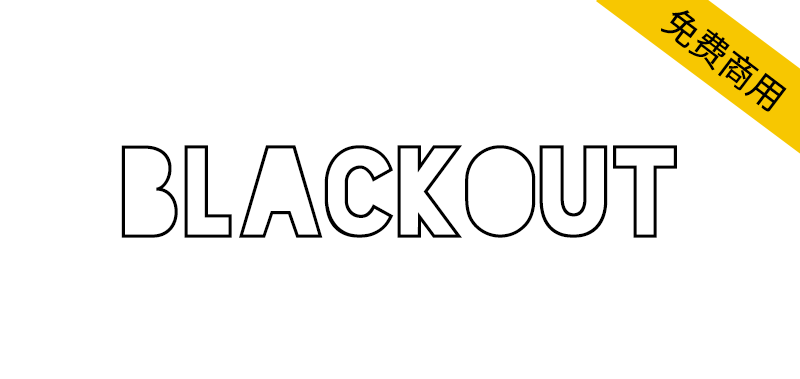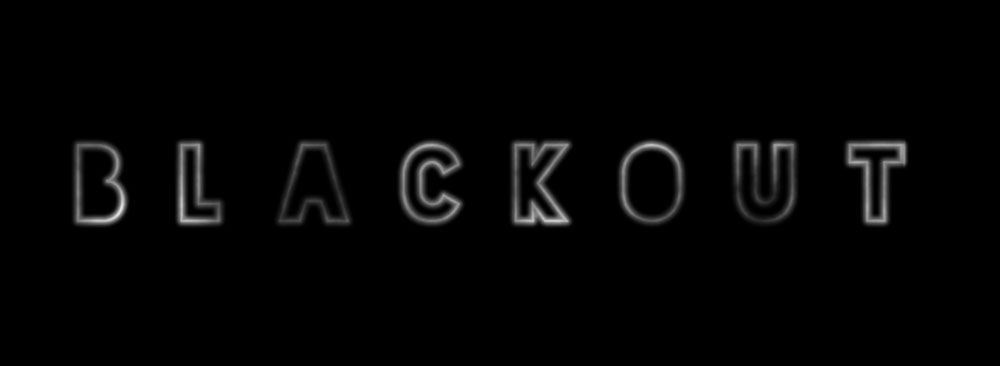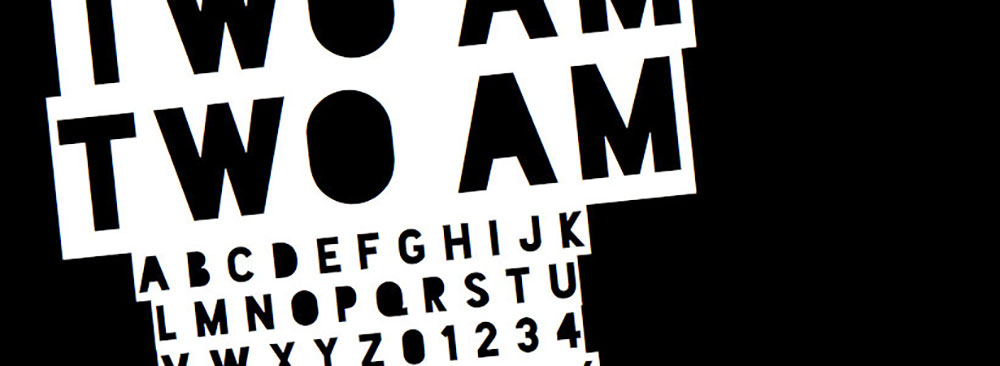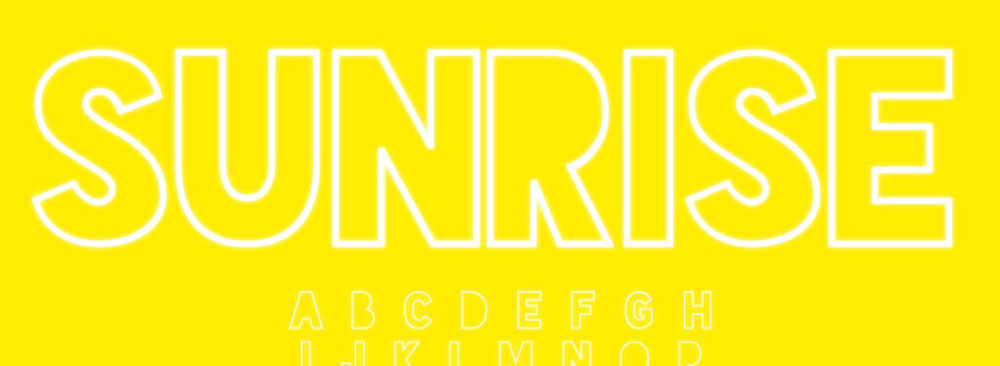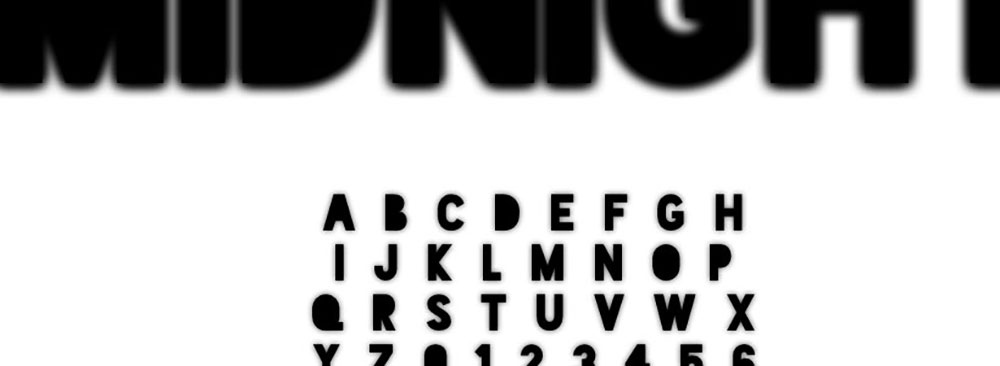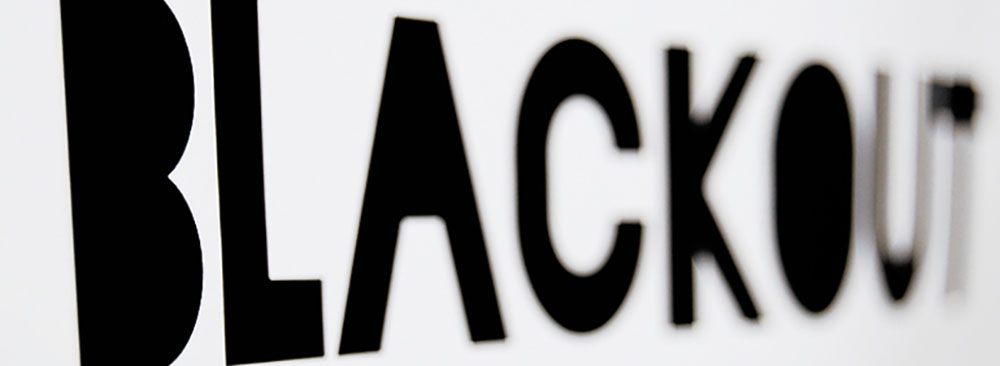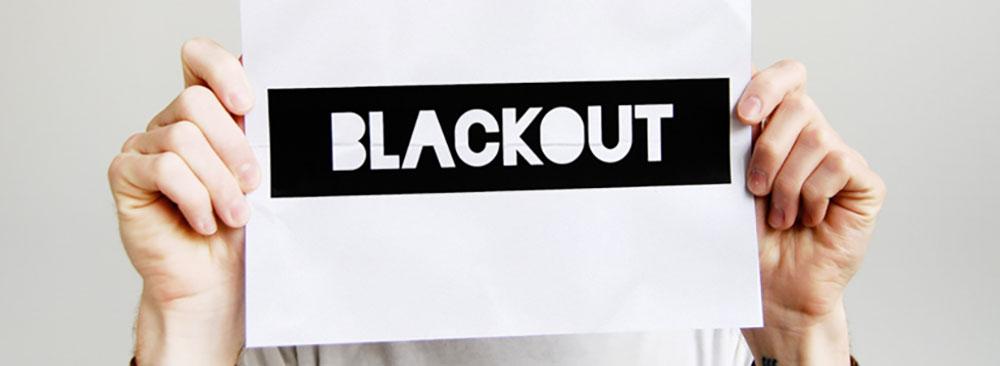
Blackout字体的灵感源自填补无衬线报纸标题的间隙,让你的作品比旁人更夺目,提供三种样式:Midnight(实心)、2AM(反白)、Sunrise(描边)。
Eats holes for breakfast lunch and dinner. Inspired by filling in sans-serif newspaper headlines. Continually updated with coffee and music. Makes your work louder than the next person’s. Comes in three styles: Midnight (solid), 2AM (reversed), & Sunrise (stroked).